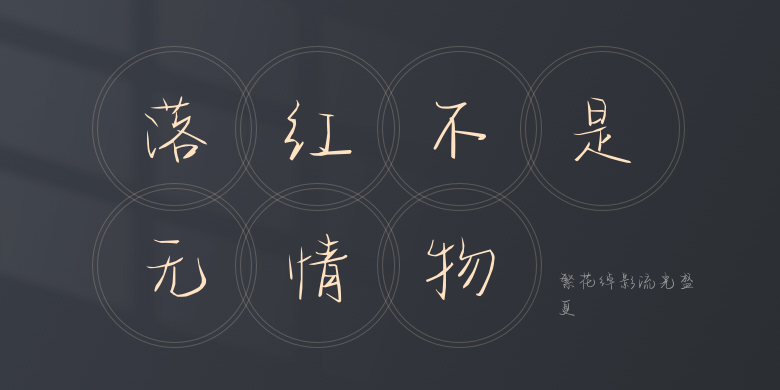
繁花绰影流光盛夏
繁花绰影流光盛夏,这款字体结构工整、笔画清晰,兼顾美观与易读性,适用于标题、正文、海报、包装、LOGO 等多种场景。字形优雅稳定,风格百搭耐看,适配日常排版与创意设计,让文字呈现更舒适、更具质感。繁花绰影流光盛夏一笔一画,皆是细节,以均衡的比例、流畅的线条打造舒适视觉体验,字形端正大气,风格简约现代。无论是商业设计、品牌宣传还是日常排版,都能轻松驾驭,让文字更有格调与力量。繁花绰影流光盛夏字体下载。